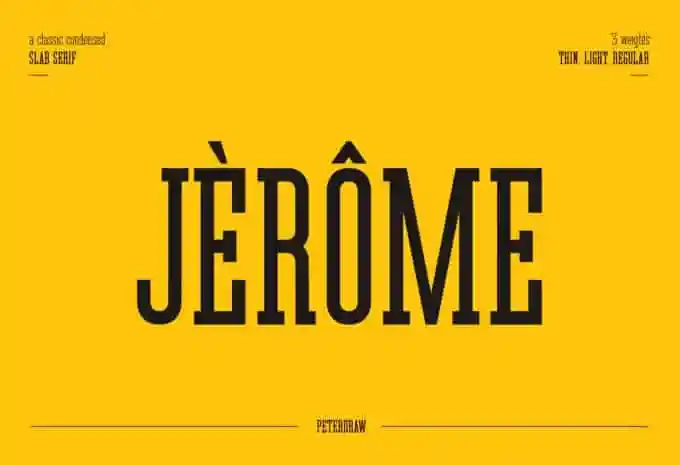
Jerome Slab Serif Font – Fonte Grátis
Jerome Slab Serif Font
A Jerome Slab Serif é uma tipografia moderna do tipo slab-serif criada para ser visualmente agradável tanto para cabeçalhos quanto para grandes trechos de texto. Desenvolvida e compartilhada pelo designer PeterDraw, ela inspirou-se em fontes compactas, fortes e sólidas, o que faz dela uma opção perfeita para aplicações variadas como logos, magazines, citações, cartazes, marcas de identidade, cartões de visita, cabeçalhos de blogs, frases artísticas ou estilos tipográficos. Com três pesos disponíveis: Espesso, Médio e Régulo, essa fonte oferece linhas fortes e sólidas, gírias agradáveis ​​e estilos impactantes que complementam perfeitamente suas aplicações. Ideal tanto para textos quanto para criação de logotipos, é uma excelente opção para vários tipos de projetos gráficos.